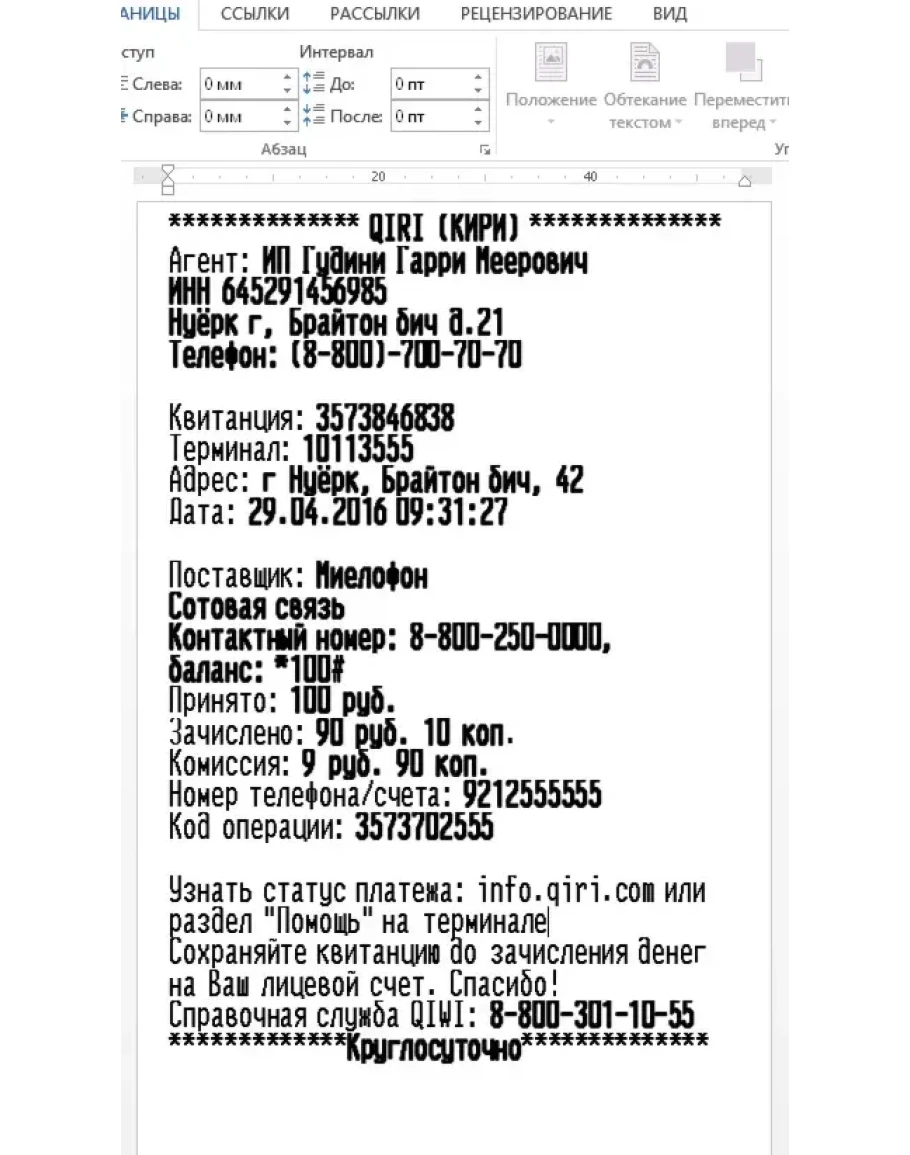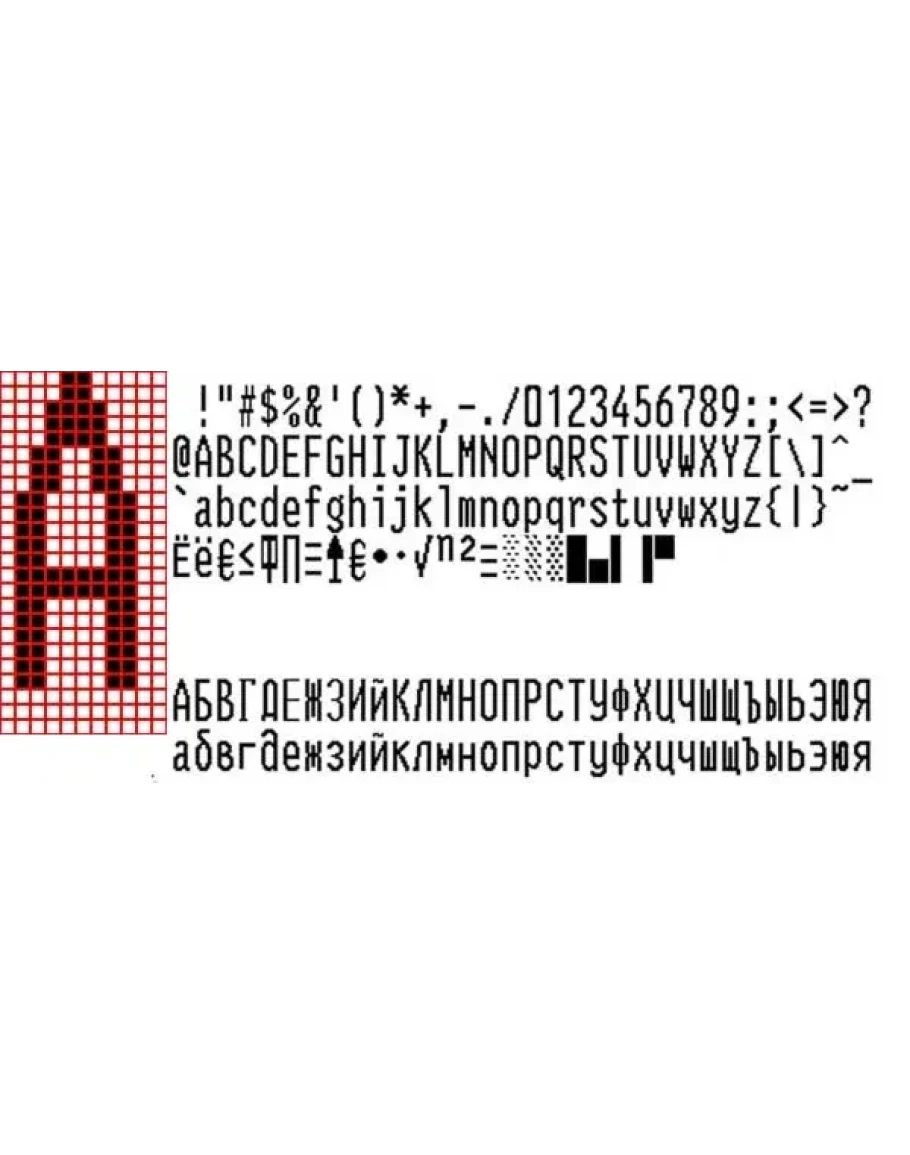
True Type (.TTF) шрифт чекового термопринтера VKP-80. Принтер используется в терминалах оплаты и торговых киосках.
Шрифт терминала оплаты VKP-80, версия 2